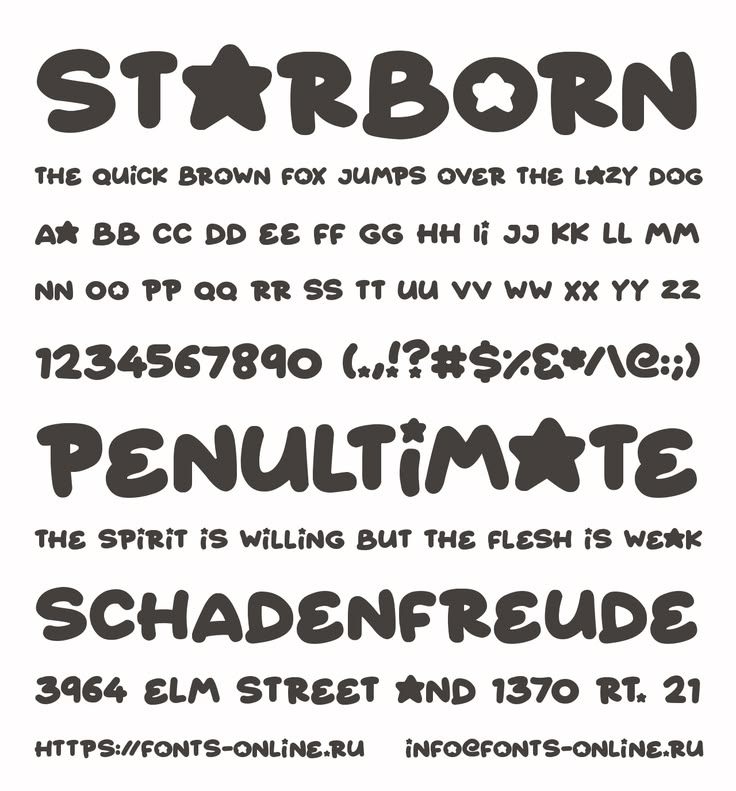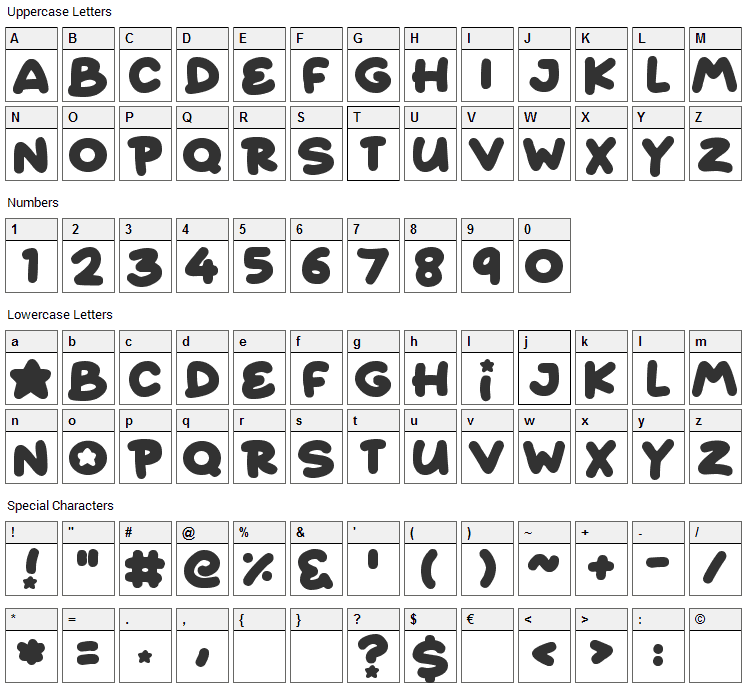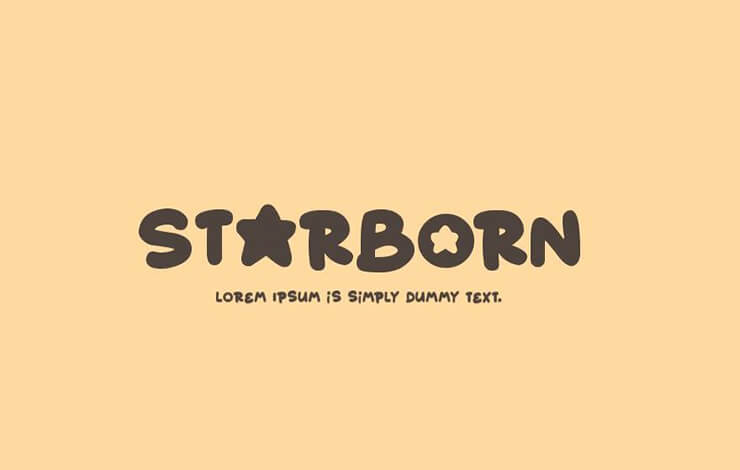
Starborn là bộ phông chữ thuộc dòng Display với cấu trúc nét dày, bo tròn mềm mại, mang lại cảm hứng vui tươi và năng động cho các bản thiết kế. Việc sử dụng font Starborn Việt hóa giúp các nhà thiết kế đồ họa và kiến trúc sư dễ dàng tạo ra những tiêu đề ấn tượng, bảng hiệu homestay độc đáo mà không gặp trở ngại về lỗi hiển thị ký tự tiếng Việt.
Đặc điểm thẩm mỹ độc đáo của dòng font Starborn Việt hóa
Khác với các kiểu chữ không chân truyền thống, Starborn sở hữu nhịp điệu hình khối vui nhộn, gợi liên tưởng đến phong cách thiết kế của các trò chơi điện tử hoặc phim hoạt hình hiện đại. Phiên bản Starborn Việt hóa được tinh chỉnh kỹ lưỡng, đảm bảo các dấu thanh phối hợp hài hòa với khung chữ chính, duy trì sự mạch lạc và tính thẩm mỹ ổn định cho văn bản.
Sự chuyên nghiệp của bộ phông này còn thể hiện qua khả năng thu hút thị giác mạnh mẽ. Dù xuất hiện trên màn hình kỹ thuật số hay in ấn thực tế trên các vật liệu như mica, alu, gỗ, các nét chữ vẫn giữ được độ sắc sảo và rõ nét. Đây là giải pháp phù hợp để định hình phong cách cho các không gian sống sáng tạo, các khu vui chơi hoặc bộ nhận diện thương hiệu cần sự đột phá và trẻ trung.
| Phân loại phong cách | Display / Rounded / Playful |
| Mục đích phù hợp | Tiêu đề Poster, Logo, Bảng hiệu, Decor |
Tư vấn trình bày: Starborn có cá tính rất mạnh và diện tích chiếm dụng lớn. Để bản thiết kế hài hòa, bạn nên sử dụng phông chữ này cho các tiêu đề chính và phối hợp cùng một phông Sans-serif mảnh cho phần nội dung thuyết minh chi tiết, giúp tổng thể bố cục trông chuyên nghiệp và thông thoáng hơn.
03 Ứng dụng đưa font Starborn vào thực tế trang trí kiến trúc
Nhờ diện mạo giàu năng lượng và tính gợi hình cao, bộ phông chữ này mang lại giá trị thực tế lớn trong khâu quảng bá và hoàn thiện các công trình hiện đại:
- Hệ thống biển hiệu cho khu vui chơi trẻ em: Những nét chữ tròn trịa của Starborn rất ăn ý khi xuất hiện trên chất liệu nhựa màu sắc hoặc gỗ tại các khu homestay nghỉ dưỡng. Phông chữ này giúp không gian trở nên gần gũi và kích thích sự khám phá của các bạn nhỏ.
- Trang trí nội thất văn phòng sáng tạo: Bạn có thể dùng font Starborn để cắt chữ nổi laser làm điểm nhấn tại phòng game, khu vực thư giãn trong văn phòng container, tạo nên một môi trường làm việc năng động và hiện đại.
- Thiết kế Poster và Banner sự kiện: Với độ hiển thị rõ nét từ xa, bộ font này giúp các thông điệp truyền thông về giải pháp nhà lắp ghép hay các chương trình ưu đãi trở nên thu hút và dễ ghi nhớ đối với khách hàng.
03 Lưu ý để bố cục font Starborn Việt hóa chuyên nghiệp
Để khai thác hiệu quả vẻ đẹp của dòng font đậm nét này mà không làm rối mắt người xem, người thiết kế nên lưu tâm một số lưu ý kỹ thuật sau:
- Nới rộng khoảng cách chữ (Tracking): Do cấu trúc chữ Starborn có phần đầy đặn, các ký tự thường trông rất sát nhau ở kích thước nhỏ. Bạn nên nới rộng khoảng cách giữa các chữ cái một chút để văn bản thông thoáng và dễ nhận diện hơn trên các bản in.
- Hạn chế viết hoa toàn bộ: Mặc dù là font Display, việc viết hoa toàn bộ cụm từ dài có thể gây cảm giác nặng nề. Bạn hãy ưu tiên sử dụng cho các từ khóa ngắn hoặc tên thương hiệu để tạo độ nhấn vừa phải.
- Lựa chọn màu sắc rực rỡ: Starborn phát huy hiệu quả thị giác cao khi phối cùng các tông màu sáng, màu gradient hoặc màu pastel, giúp tôn vinh tinh thần trẻ trung và sáng tạo của bộ chữ.